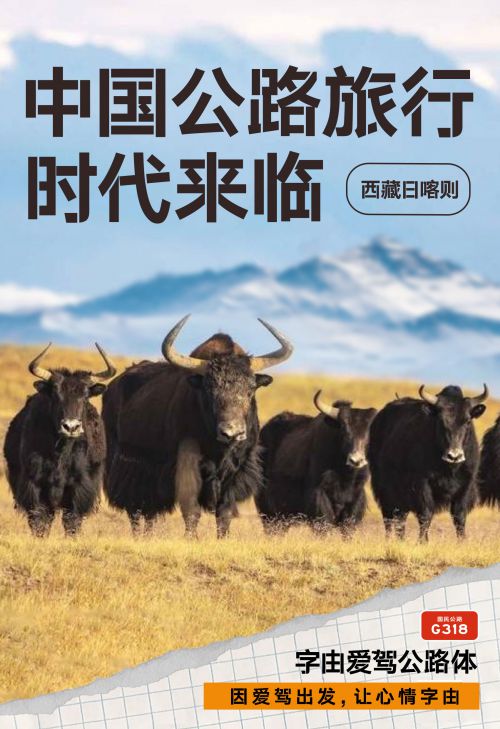
字由爱驾公路体
字由爱驾公路体是一款以公路标识风格为灵感的无衬线中文字体,强调高辨识度、远距离可读性与稳健的视觉气质。适用于品牌标识、导航界面、海报、广告牌以及交通信息等需要清晰传达信息的场景,兼具现代感与实用性,便于在多媒体媒介中保持一致的视觉语言。 秉承着打造中国人自己的世界级公路IP的愿望,字由与爱驾传媒一起走上G318国道,以公路视觉元素中用以传达信息的“公路文字”作为灵感,合作发布了联名字体字由爱驾公路体。
卢鑫亚
90后字体设计师,曾获第二届字体之星评委奖,最具商业潜力奖,第三届字体之星评委奖。